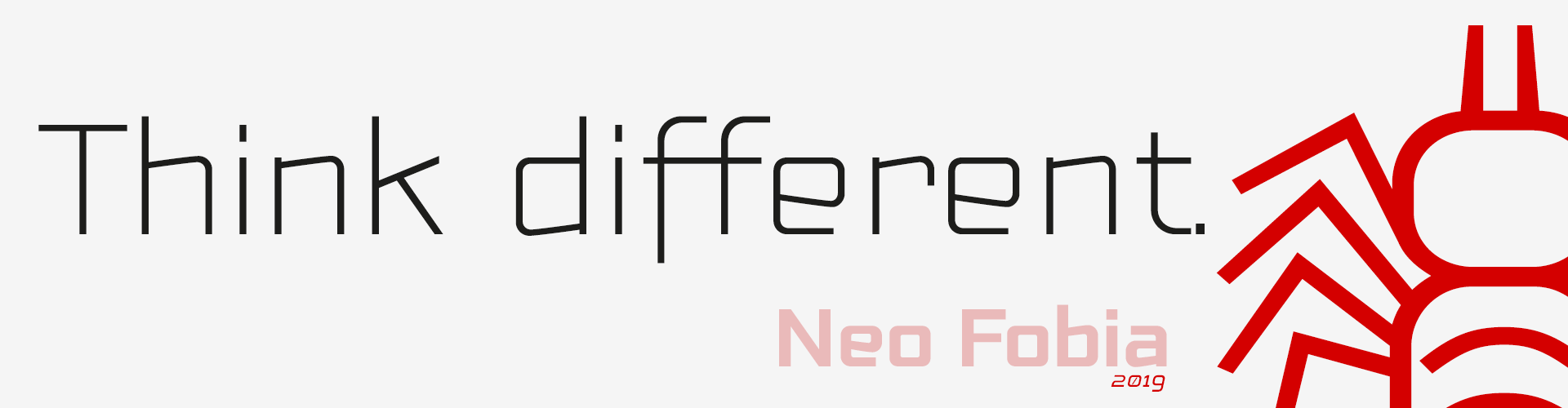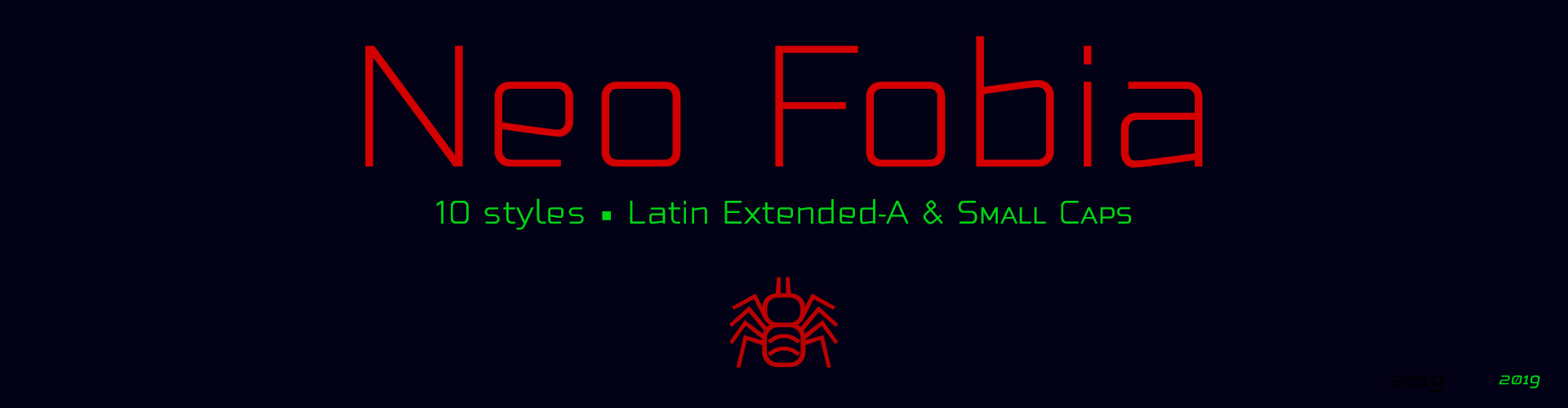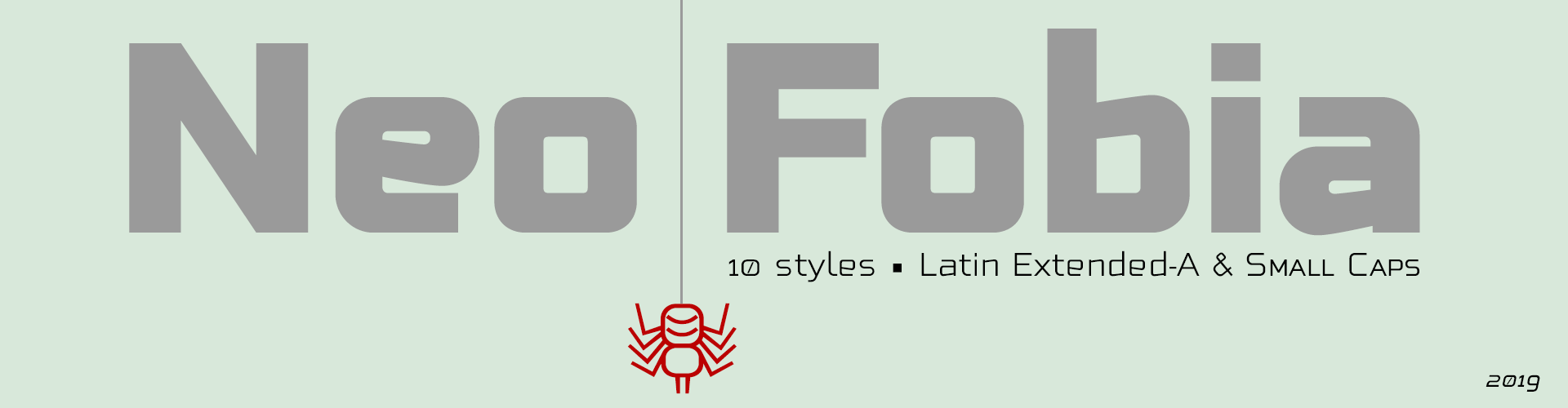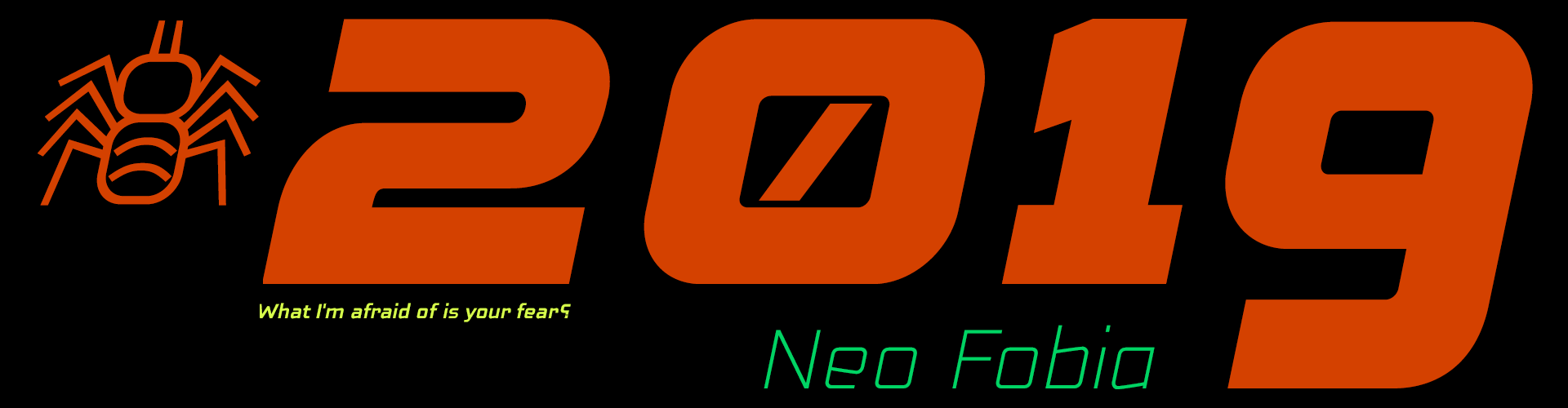
Techno futuristic
Estilo: Sans Serif, Geometric, Rounded, Small Caps
Proporción: Extra Light, Light, Regular, Bold, Extra Bold & Italics
Año de publicación: 2019.
Funciones OpenType: Additional languages, All Alternates, Alternate Annotation Forms, Bitcoin, Capital Spacing, Contextual Alternates, Denominators, Discretionary Ligatures, Extended Fractions, Historical Forms, Inferiors, Kerning, Localized Forms, Numerators, Oldstyle Figures, Ordinals, Scientific Inferiors, Slashed Zero, Small Capitals, Small Capitals From Capitals, Standard Ligatures, Subscript, Superior letters, Superiors, Superscript.
Neo Fobia esta inspirada en las fuentes geométricas de principios del siglo XX inspiradas en la escuela Bauhaus y está especialmente diseñada para uso en cualquier tamaño tanto para pantalla como en impresión publicitaria y editorial.
Neo Fobia es una tipografía muy versátil para diseño gráfico y publicidad, podrás usarla en diseño de posters, vídeo juegos, títulos de cine, logotipos, diseño de marca, etc.